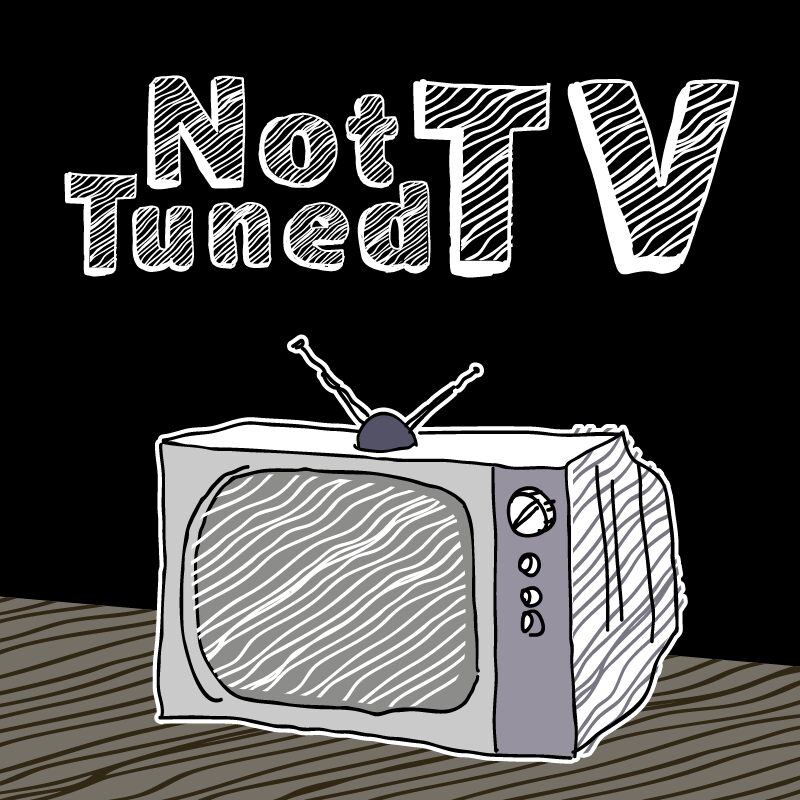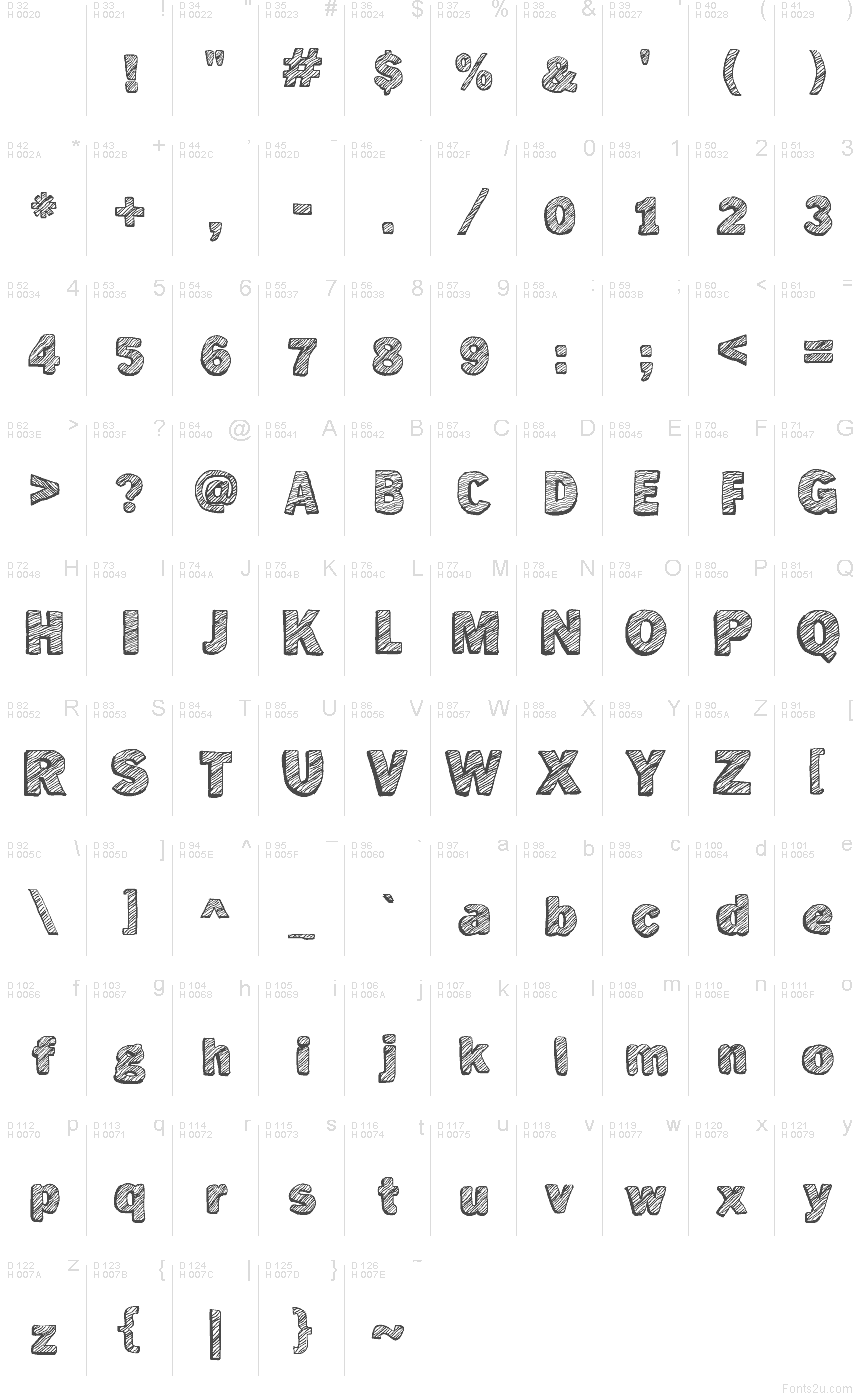
Not Tuned TV von Galdino Otten Fonts ist eine kostenlose, handgezeichnete Cartoon-Display-Schrift mit klobigen, ungleichmäßigen Buchstaben und einem unruhigen, skizzierten Finish. Ihre abgerundeten Formen neigen sich leicht und schwellen an, als wären sie aus Pappe geschnitten statt auf einem strengen Raster aufgebaut. Dichte diagonale Schraffuren füllen die Striche und verleihen den Buchstaben das Aussehen einer getuschten Skizze.
Kinderunterhaltung und Comic-Grafiken eignen sich besonders gut für diesen rauen, verspielten Stil, der Plakattitel und Spielgrafiken zu einem Teil der Illustration machen kann. Dieselbe krakelige Textur könnte Verpackungen oder Merchandise-Artikel für einen schrägen Snack, ein Spielzeug oder eine Jugendmarke mit einer bewusst handgemachten Identität prägen.
Not Tuned TV